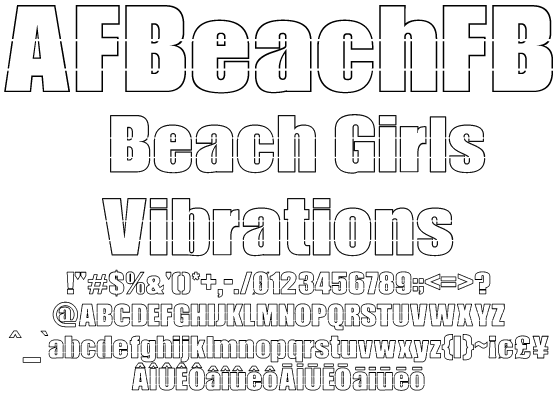
スピード感、真夏なスリット欧文フォント AFBeachFB
AFBeachFB
60年代のサーフィンをイメージし、アルファベットと数字にスリットを刻んだ太ゴシックの袋文字欧文です。スピード感をイメージしたい場面でご利用ください。同人系、コミック、アニメ、ゲーム、パンフレット、リーフレット、フライヤー、ファッション系コンテンツに使えるフォントです。日本のローマ字表記で使われる訓令式やヘボン式で扱う Ô や Ō を収録、人名地名へのアプローチもリアルです。